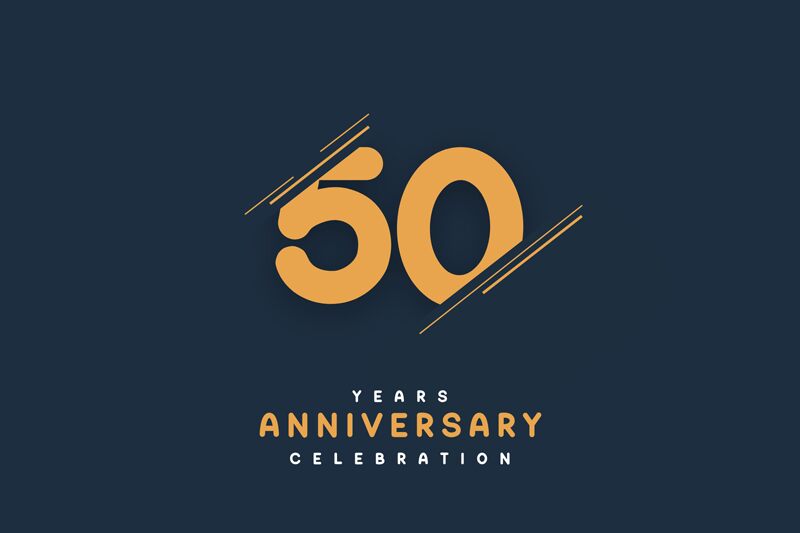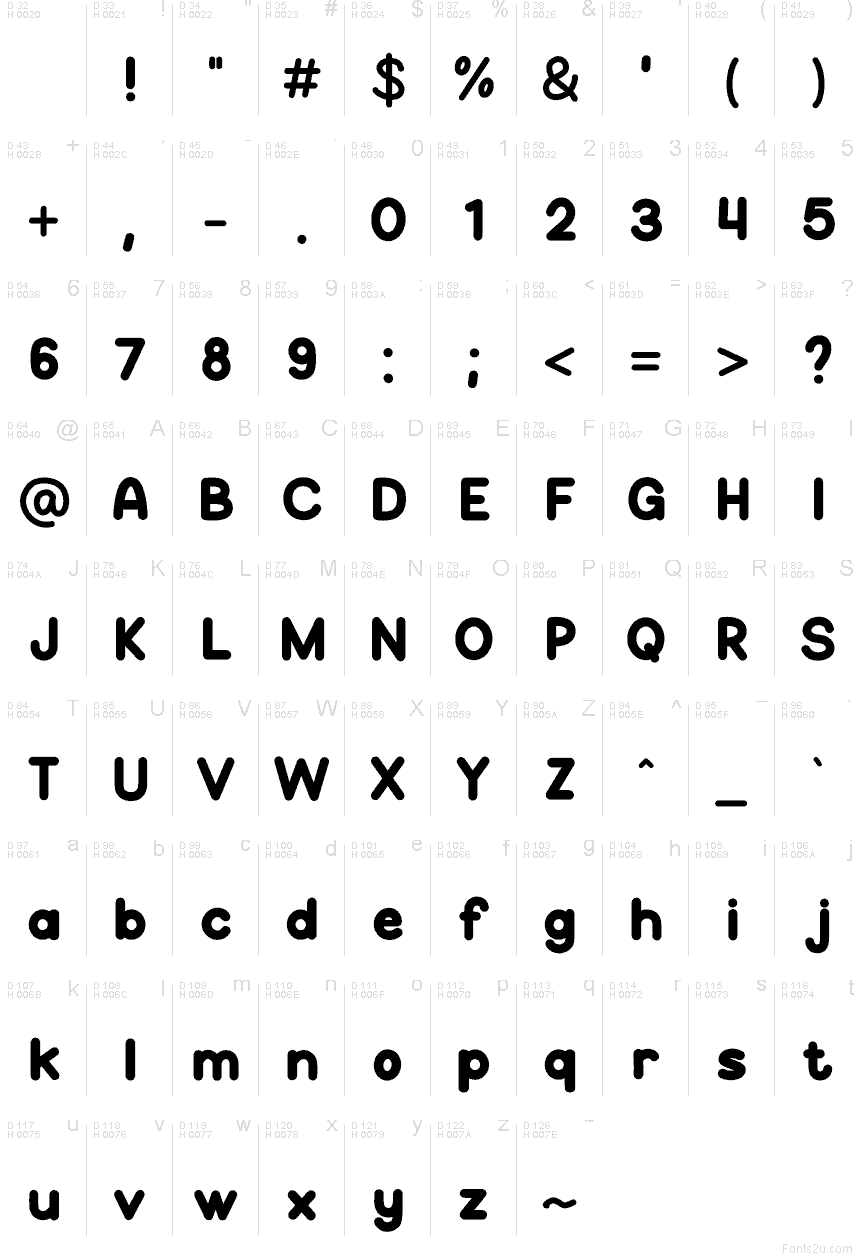
Lolla Sans
Lolla Sans je bezplatné kreslené písmo typu display s mäkkým, robustným rytmom, ktorý vracia spomienku na bezstarostnosť detských nápisov v retro štýle. Jeho hrubé, zaoblené tvary pôsobia živo a priateľsky – písmená vyzerajú ako nafúknuté, ale pritom nestrácajú čitateľnosť a neprepadajú karikatúre.
Je to prirodzená voľba pre obaly pochutín, značky hračiek, párty pozvánky, hravé záhlavia aplikácií alebo náhľady na YouTube, kde krátke slovo potrebuje skôr hrejivosť než dokonalé vyhladenie. Skvelo sa hodí aj na nálepky a rýchle návrhy log, pretože znaky sú široké, kompaktné a dostatočne jednoduché na to, aby držali pokope ako výrazný grafický prvok.